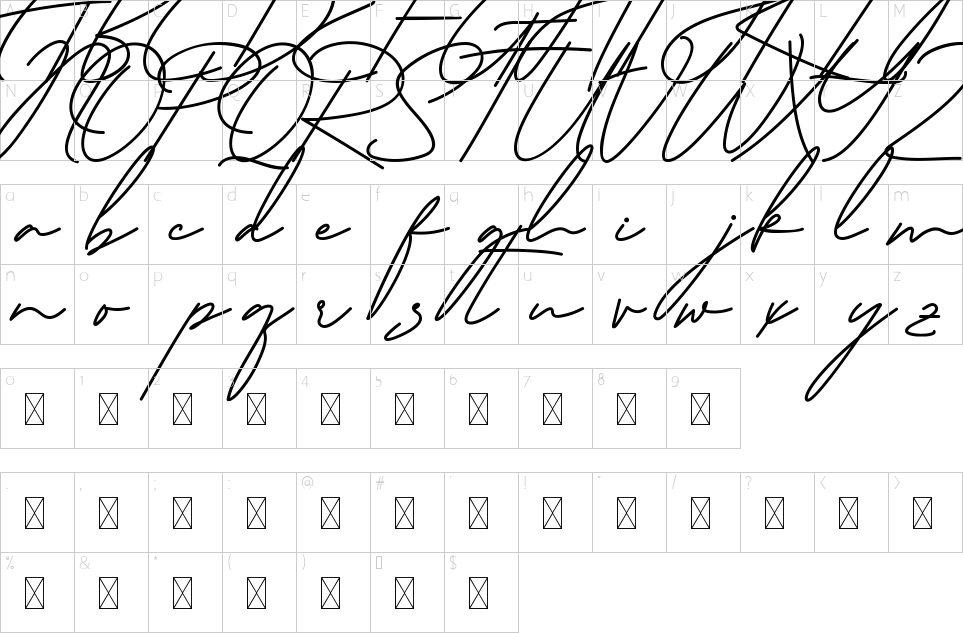
Marlines é uma fonte moderna e elegante que combina facilmente em uma variedade de projetos gráficos. Desenvolvida pelo RaisProject, esta fonte conta com uma ampla gama de caracteres e é extremamente versátil. Com 2.937 downloads, Marlines já se tornou um favorito entre os criadores de design. Suas linhas leves e equilibradas tornam-na ideal para criar textos legíveis e profissionais. Se você está buscando uma fonte que se adequa a várias aplicações, Marlines é uma excelente escolha. Sem dúvida, uma fonte gratuita de alta qualidade que merece uma chance.